Двусторонняя печать на тонкой бумаге: как проверить рукописный шрифт
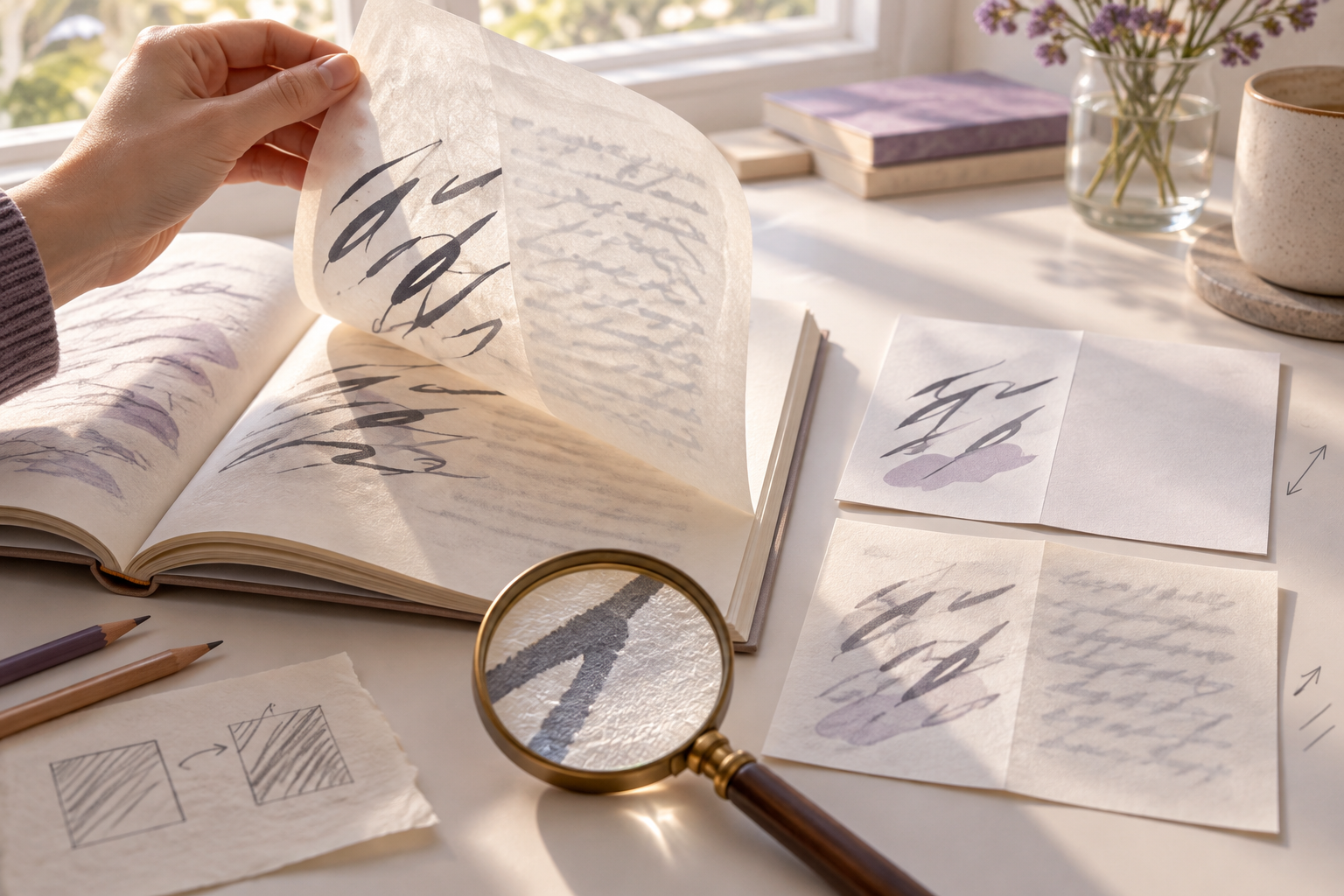
Если текст на обороте листа просматривается сквозь бумагу, рукописный шрифт может казаться менее чётким, хотя сами буквы нарисованы и набраны правильно. Проблему нужно проверять на физическом образце, с двух сторон и в условиях будущей печати. Так вы поймёте, что менять: бумагу, плотность набора, заливку или сам рисунок букв.
Что именно просвечивает: бумага или краска
Сначала различите два явления. При просвечивании (show-through) на лицевой стороне виден текст с оборота, но краска не перешла на неё физически. При пробивании краски (strike-through) пигмент или связующее проникли через лист, поэтому на обороте либо лицевая сторона получает реальные пятна и ореолы. В разговоре их часто объединяют словом «просвет», но причины и способы исправления отличаются.
Непрозрачность бумаги описывает, насколько лист мешает видеть изображение за ним. Это свойство можно измерить: ISO 2471 задаёт метод определения непрозрачности бумаги и картона диффузным отражением. Сам стандарт не говорит, какая бумага подойдёт именно вашей книге: оценка зависит от бумаги, краски, площади заливки, кегля и расположения строк на двух страницах. Поэтому паспортная характеристика помогает сравнить образцы, а окончательный выбор требует пробы.
Если оборот виден, но краска не проступила, проверьте непрозрачность, оттенок и толщину листа. Если на обратной стороне есть ощутимый окрашенный след, масляное пятно или локально изменённая поверхность, попросите типографию проверить режим печати и совместимость материала с краской. Не пытайтесь решить второй случай одним изменением шрифта: его контуры не отвечают за проникновение краски.
Почему рукописный шрифт особенно чувствителен к обороту
Рукописное начертание часто сочетает тонкие соединительные штрихи, небольшие просветы внутри букв и неравномерные интервалы. На просвечивающем листе строки с двух сторон визуально складываются: тонкая петля может попадать на вертикаль текста с оборота, а мелкое отверстие внутри «а» или «о» — теряться на фоне соседнего штриха. Читатель замечает не отдельный дефект буквы, а общую сероватую или беспокойную фактуру страницы.
Это не означает, что любой рукописный шрифт нельзя печатать на тонкой бумаге. Важны сочетание кегля, насыщенности текста, длины строк и «зеркального» расположения набора. Если строки лицевой и оборотной стороны совпадают по горизонтали, фон может казаться плотнее. Если строки смещены, просвечивающие буквы иногда хуже читаются, потому что формируют второй ритм рядом с основным.
Смотрите на страницу в масштабе реального чтения, а не только на увеличенный фрагмент. Увеличение полезно для поиска конкретного сбоя в контурах, но не показывает, насколько заметен обратный текст с обычного расстояния. Проверяйте и плотный абзац, и короткую подпись, и участок с заголовком: крупные тёмные буквы могут просвечивать сильнее длинного текста.
Подготовьте пробу, которая отвечает на вопрос
Сравнение будет полезным, если менять по одному условию. Попросите у типографии несколько подходящих вариантов бумаги и уточните, можно ли получить тестовый оттиск на каждом материале. Если тираж планируется офсетным способом, важнее всего проба, воспроизводящая выбранную бумагу и производственный процесс; распечатка на офисном принтере годится для проверки набора, но не гарантирует такого же результата.
Подготовьте один тестовый разворот, а не набор разрозненных слов. На нём нужны основные строчные буквы, цифры, знаки препинания, самый мелкий планируемый кегль, полужирные места и обычный текст. Добавьте реалистичный фрагмент с тем же числом строк и примерно той же плотностью, что будет в изделии. Для рукописного шрифта полезно включить повторяющиеся пары и слова с петлями: например, «шалаш», «минимум», «длинная линия». Это помогает увидеть и плотность текстуры, и конкретные слипшиеся просветы.
В печатной пробе следует сохранять одинаковыми размер букв, начертание, цвет текста, межстрочное расстояние, поля и настройки вывода. Не сравнивайте одну бумагу с короткой строкой, а другую — с залитой страницей. Если в макете будут изображения, фоны или цветные плашки, добавьте характерный фрагмент: они могут изменить общий визуальный вес страницы.
Попросите отпечатать тест двусторонне в правильной ориентации. Отдельная односторонняя страница не покажет, как две текстовые стороны взаимодействуют. Если типография ещё не готова к физической пробе, распечатайте макет дома на каждом листе, отметив, что это предварительное сравнение, а не утверждение производственного результата.
Как сравнить листы и записать наблюдения
Положите образцы рядом и подписывайте каждую бумагу кодом или названием из коммерческого предложения. Смотрите на них при одинаковом освещении и подложке; менять место и свет во время сравнения не нужно. Сначала оценивайте лицевую сторону с нормального расстояния, затем переверните лист и посмотрите, насколько чётко читается оборот. В конце разберите увеличенные фрагменты, чтобы найти буквы, на которых сбивается чтение.
Просвечивание проверяют на двусторонней печатной пробе: сначала отделяют свойства бумаги от дефекта печати, затем оценивают страницу в реальном масштабе и фиксируют конкретные проблемные места. Только после такой проверки стоит менять бумагу, макет или само начертание. Если вы создаёте свой почерк как шрифт, подготовьте характерный тестовый текст в Fontgenerator, а затем используйте один и тот же образец при сравнении бумаги и пробных оттисков.